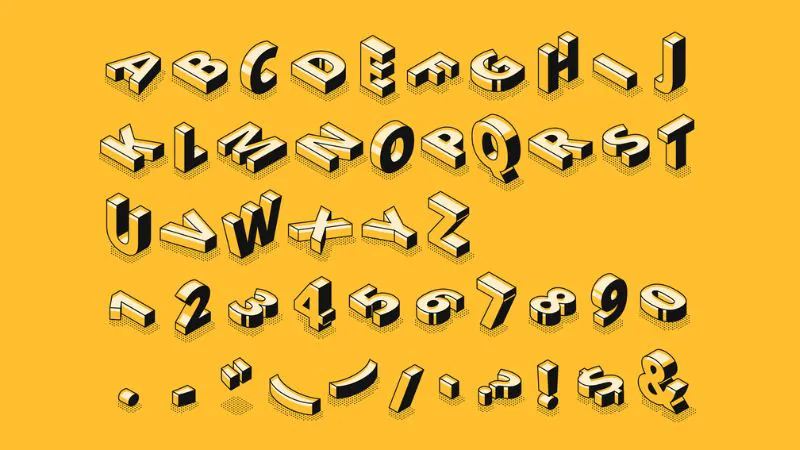
Font chữ 3D là nhóm các phông chữ Display được thiết kế tích hợp sẵn hiệu ứng nổi khối, chiều sâu, đổ bóng hoặc phối cảnh isometric, giúp các dòng tiêu đề mang lại cảm giác không gian ba chiều vô cùng sống động mà không cần qua các bước dựng hình phức tạp. Với sự đa dạng từ phong cách hoạt hình ngộ nghĩnh đến các khối kim loại sắc sảo, nhóm phông chữ này là lựa chọn hoàn hảo cho các thiết kế bao bì bánh kẹo lễ hội, hộp quà Tết, poster sự kiện và các ấn phẩm quảng cáo cần sự bùng nổ thị giác. Doozypack.vn cung cấp link tải trọn bộ font chữ 3D đẹp chuẩn kỹ thuật, giúp bạn sở hữu kho phông chữ nổi khối ấn tượng, hỗ trợ tiếng Việt mượt mà để hiện thực hóa mọi ý tưởng thiết kế phá cách.
Đặc điểm thẩm mỹ độc đáo của bộ font chữ 3D
Font chữ 3D không đi theo sự phẳng lặng của các phông chữ văn bản thông thường; nó tạo ra một không gian thị giác có chiều sâu, mang lại trải nghiệm xúc giác giả lập (tactile feeling) đầy thú vị cho người xem.
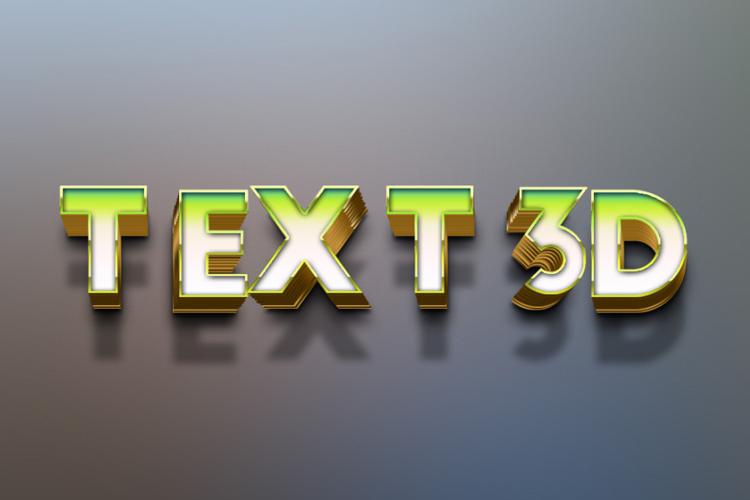
Hiệu ứng nổi khối chiều sâu và cảm giác xúc giác (Tactile)
Đặc trưng lớn nhất của Font chữ nổi 3D là cấu trúc chữ có phần thân chính kết hợp cùng lớp bóng đổ (shadow) hoặc khối đùn (extrusion) phía sau. Thiết kế này tạo ra ảo ảnh quang học như thể các con chữ đang nhô hẳn lên khỏi bề mặt giấy. Khi đặt phông chữ này làm tiêu đề trên bao bì, thương hiệu của bạn sẽ ngay lập tức chiếm trọn tâm điểm chú ý, tạo cảm giác về một sản phẩm cao cấp, có đầu tư bài bản và cực kỳ sinh động.
Sức hút thị giác vượt trội cho các tiêu đề sự kiện và lễ hội
Các kiểu chữ 3D đẹp thường sở hữu độ dày nét lớn, màu sắc rực rỡ và phong cách trang trí lộng lẫy. Sự xuất hiện của chúng trên các ấn phẩm bao bì quà tặng Trung thu, Giáng sinh hay quà Tết giúp truyền tải không khí tưng bừng, rộn ràng của mùa lễ hội, kích thích tâm trạng vui vẻ và quyết định mua hàng của người tiêu dùng.
Ưu điểm nổi bật của bản phông chữ 3D Việt hóa
Khi ứng dụng các phông chữ hiệu ứng khối nổi vào thị trường trong nước, sự chỉn chu về dấu câu là yếu tố quyết định đến tính chuyên nghiệp của ấn phẩm:
- Khắc phục triệt để lỗi dấu tiếng Việt: Phiên bản Việt hóa đã được đội ngũ thiết kế trau chuốt thủ công từng dấu câu. Các dấu sắc, huyền, hỏi, ngã, nặng được vẽ với khối 3D và bóng đổ đồng điệu cùng thân chữ gốc, không gây cảm giác chắp vá hay làm mất đi tính không gian của phông chữ.
| Nhóm Font 3D | Đặc điểm thị giác | Ứng dụng đề xuất tại Doozypack.vn |
| 3D Cartoon / Bubble | Phúng phính, bóng bẩy, ngộ nghĩnh | Bao bì bánh kẹo trẻ em, hộp đồ chơi, sticker sự kiện. |
| 3D Metallic / Block | Khối hình học, góc cạnh, uy lực | Tiêu đề hộp quà Tết, nhãn chai rượu, hộp sản phẩm cao cấp. |
| 3D Retro / Shadow | Đổ bóng cổ điển, phong cách thập niên 70 | Bao bì đồ ăn vặt, túi giấy thời trang năng động. |